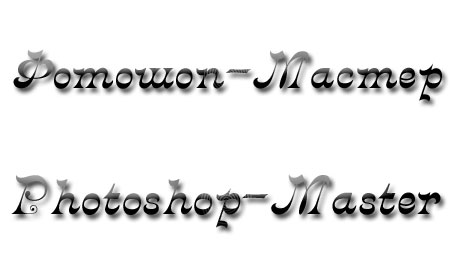
Очень классный шрифт спасибки вам))))
Классный шрифт, спасибо вам!
Красивый шрифт! Спасибо!
прикольно!!!!!!!!!!
Спасибо! Интересный шрифт. Изящный, без излишек.
Стильный шрифт. Красиво!
отличный шрифт, то что искала, спасибо!
классный шрифт!
Симпатичный шрифт. Спасибо.
Спасибо - шрифт хороший :)
Очень симпатичный шрифт! :)
Мне тож нрав.